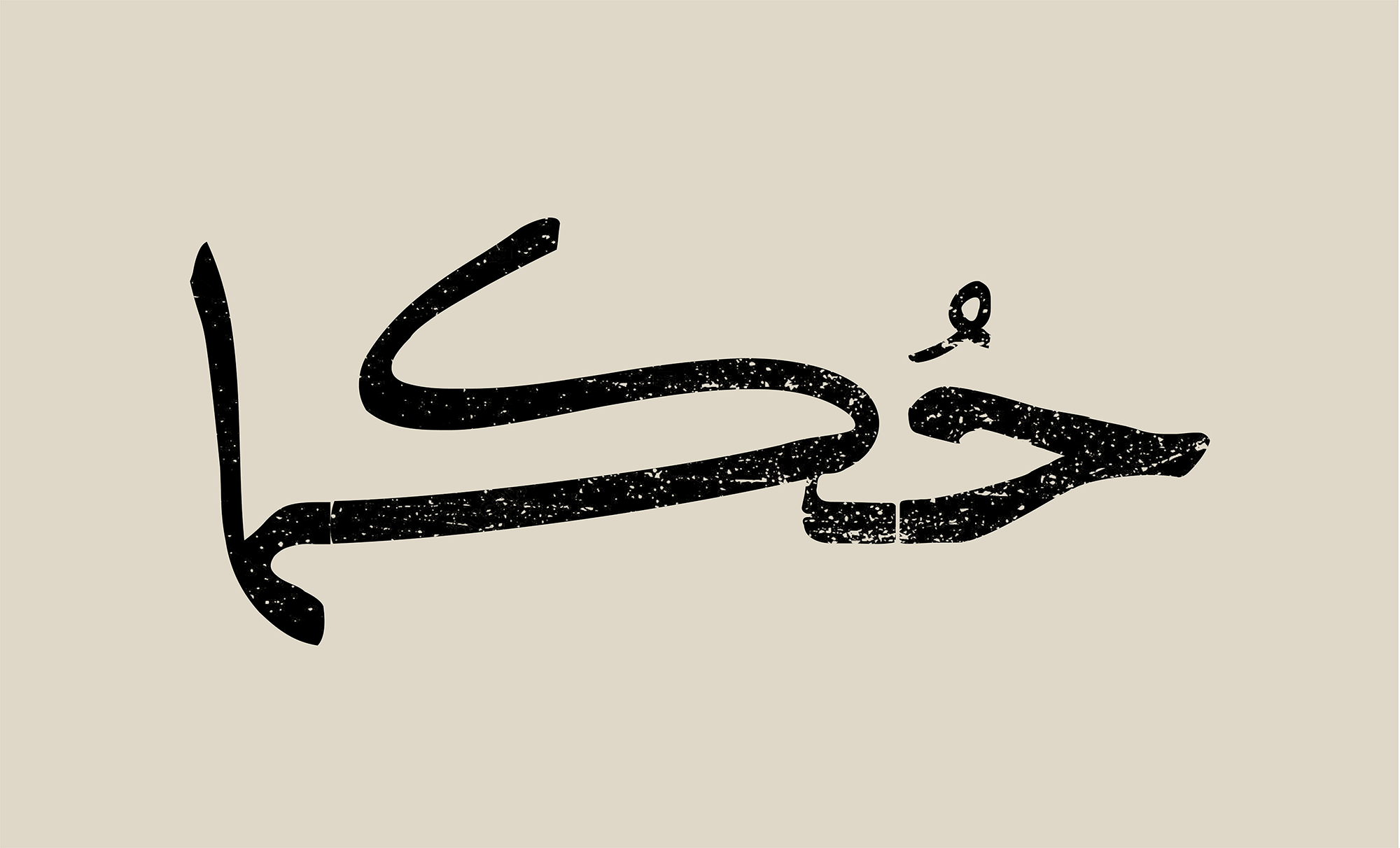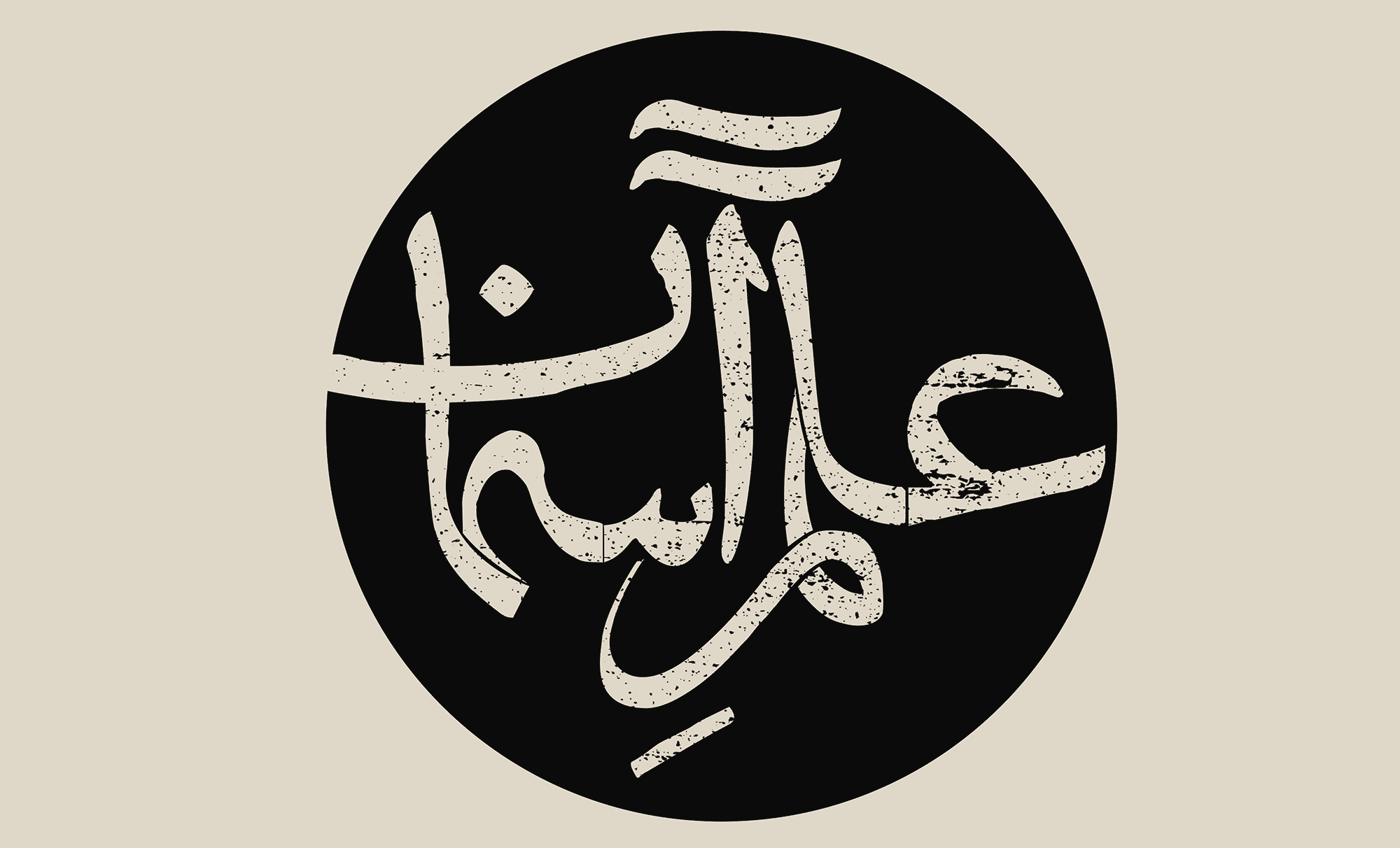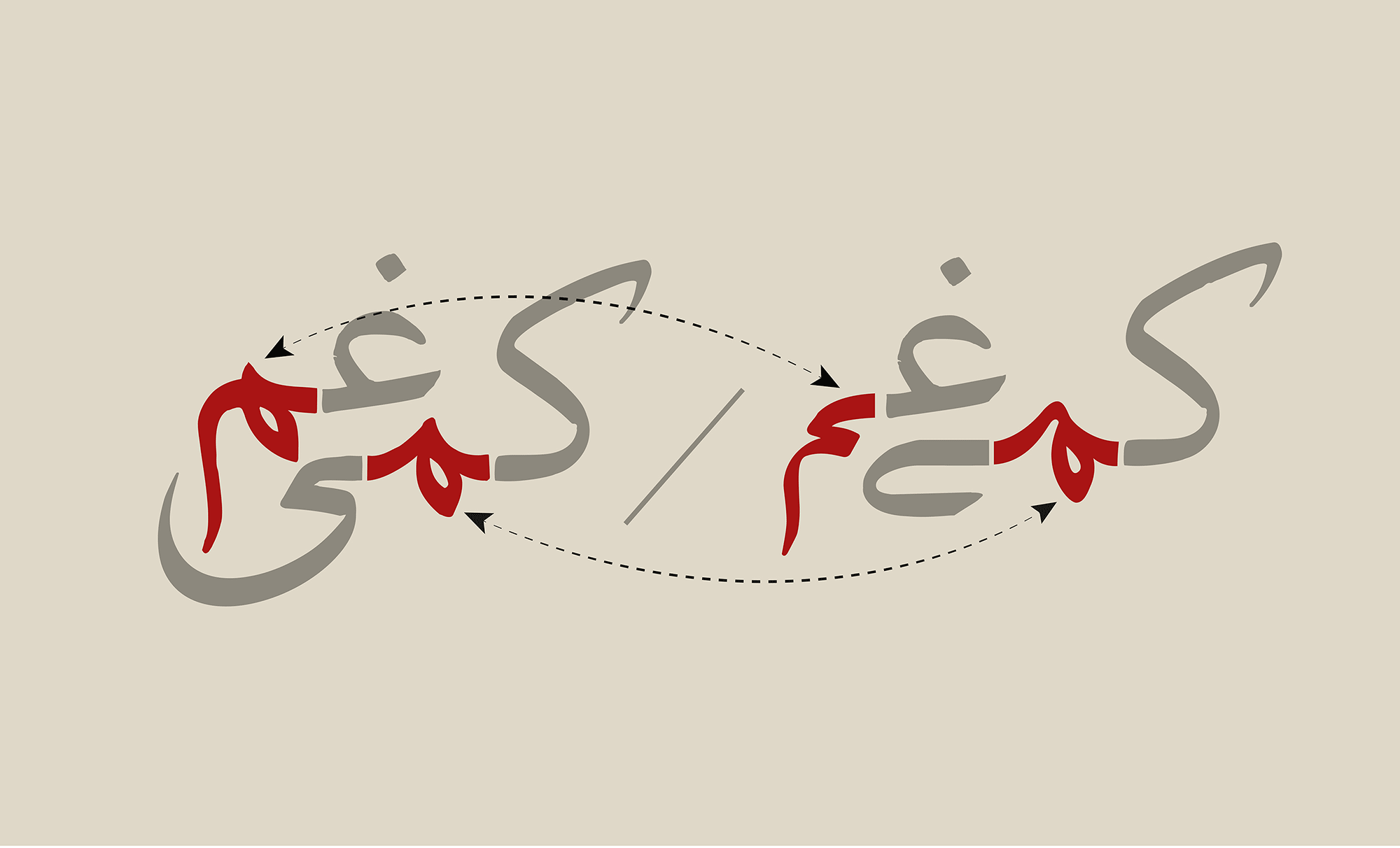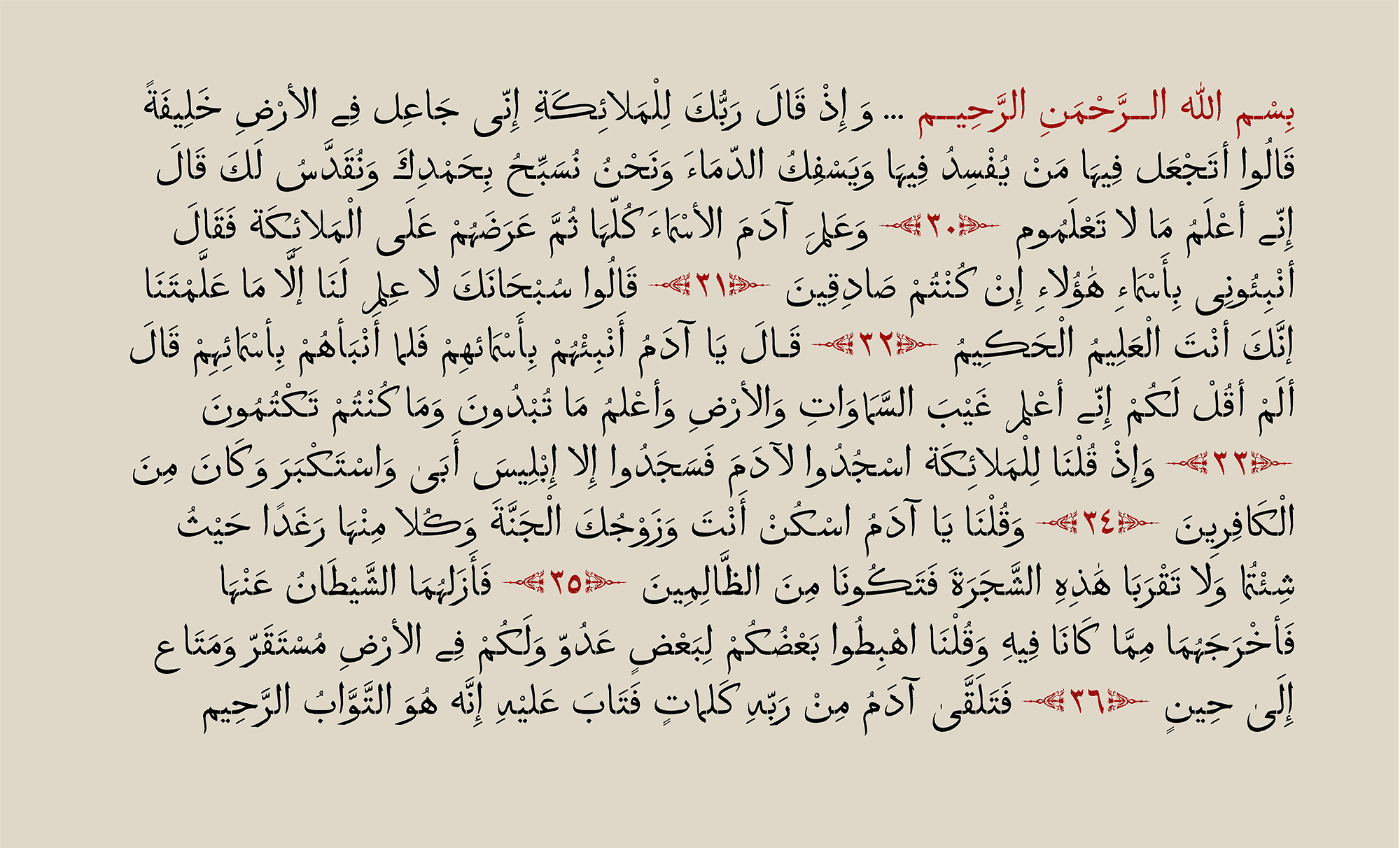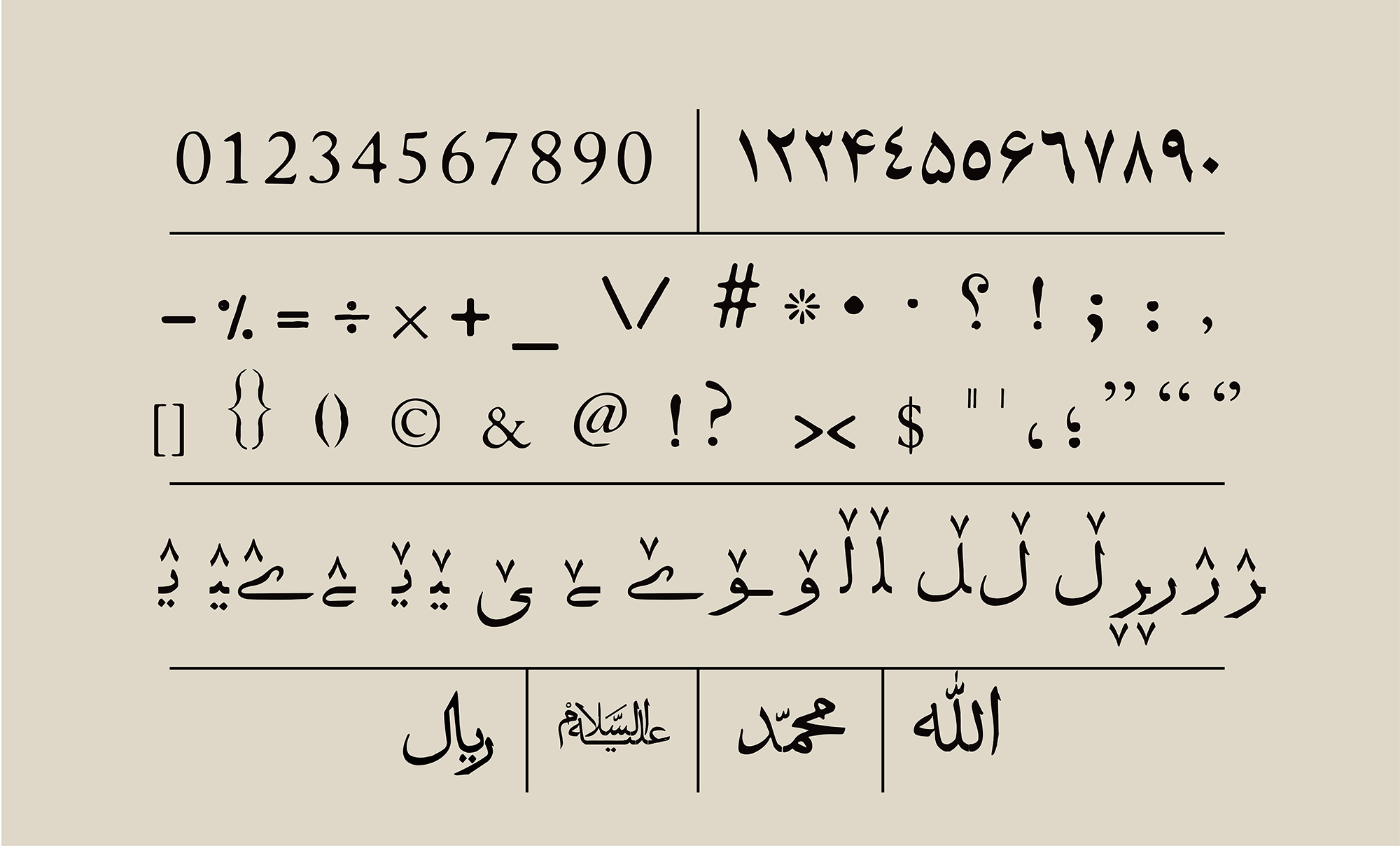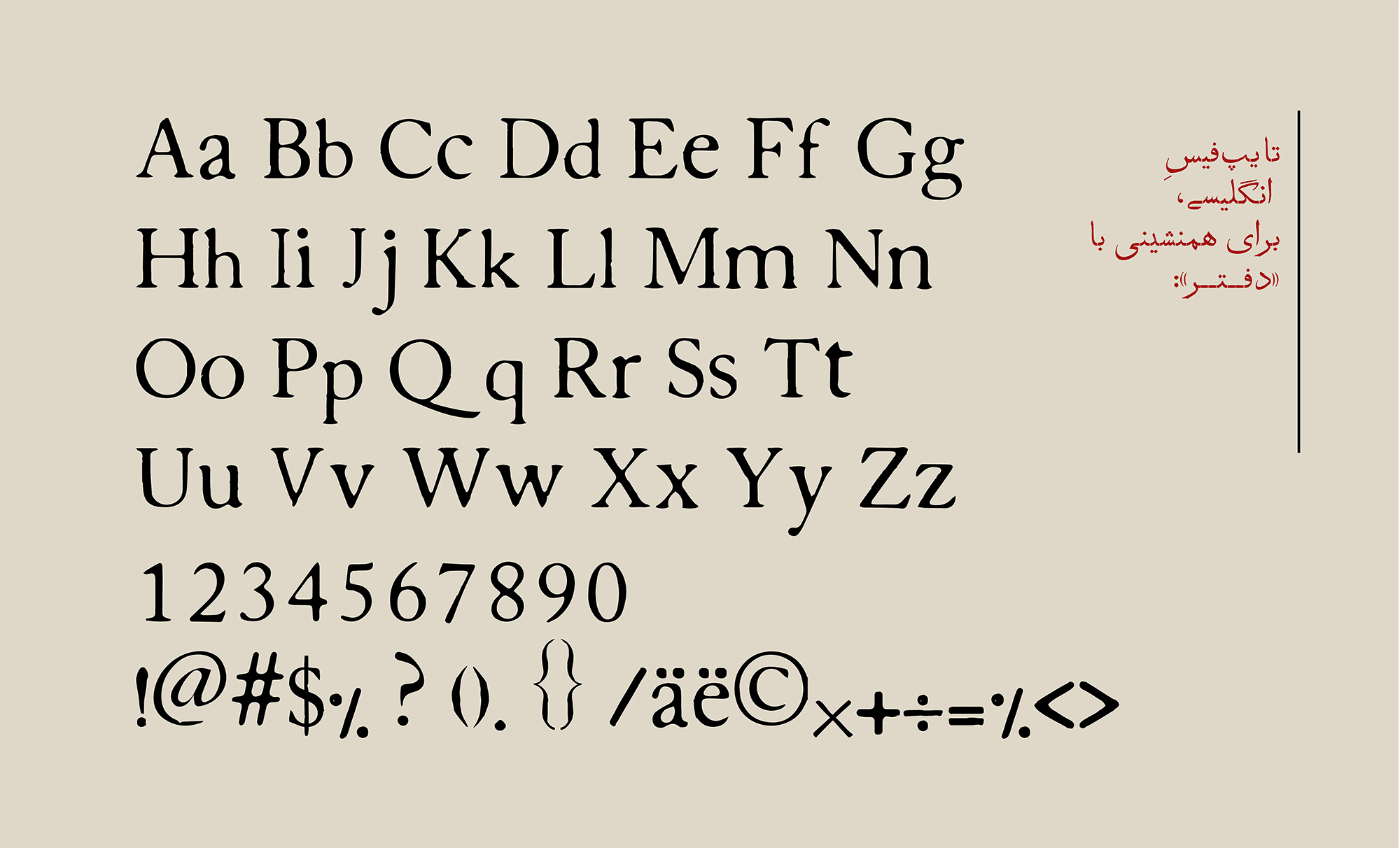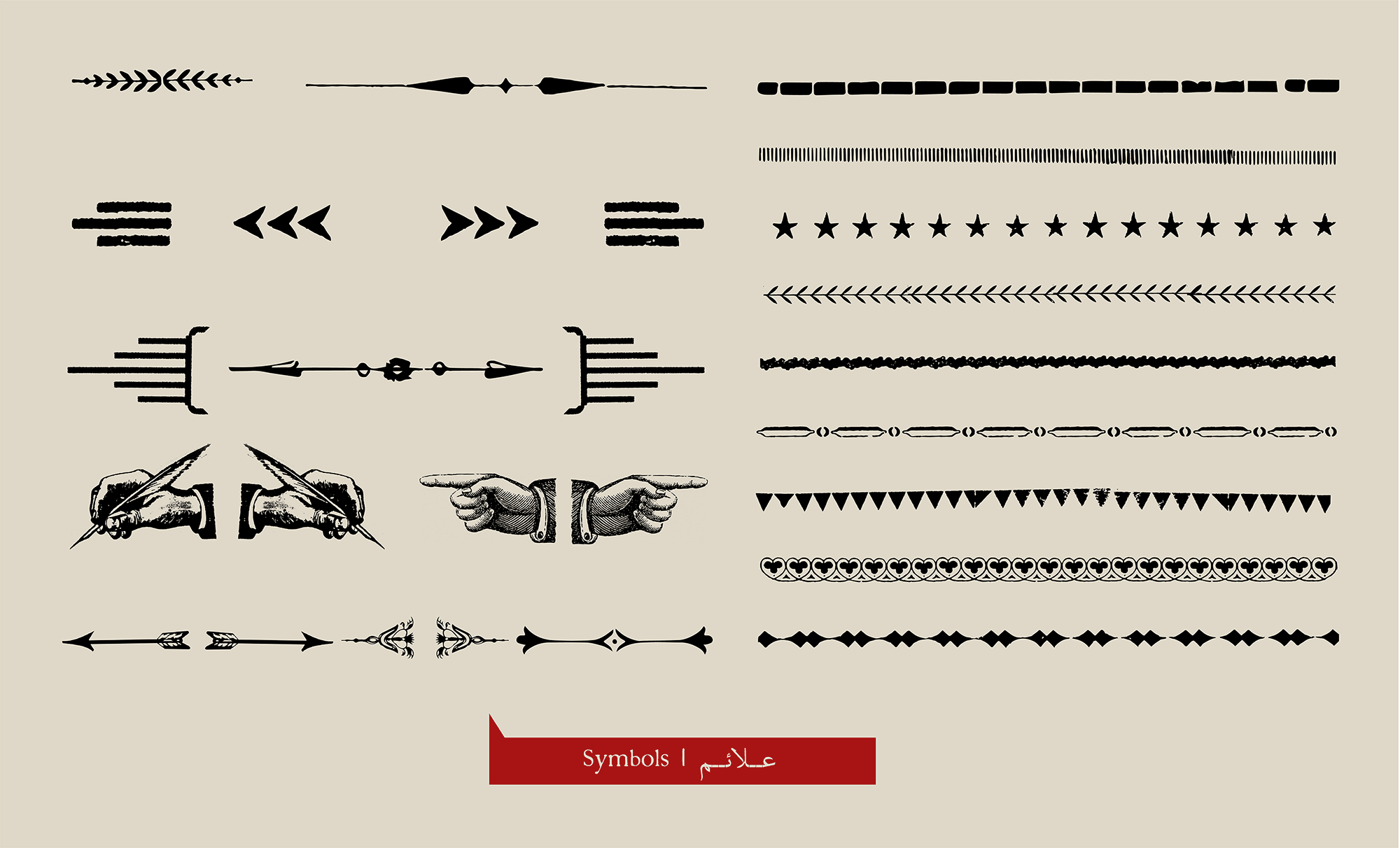
فونت دفتر در سه زبان فارسی، انگلیسی قابل استفاده است.
حروفِ تازهی کهنه!
طراحان گرافیک، طراحان فضای مجازی و وبسایت، ناشران، مطبوعات، طراحان صحنه، هنرمندان و همهی آنها که به نوعی با فونتهای فارسی سروکار دارند، همواره با کمبودِ حروفی با حال وهوای قدیمی، برای ساخت فضاهای نوستالژیک مواجه هستند.بههمین دلیل، هر وقت پای اِلقایِ حسّی قدیمی به کمک یک فونت به میان میآید، یا باید بیخیالش بشویم یا با دستکاریِ نمونههای موجود، عجالتاً کارمان را راه بیندازیم!
برشهایی از چند روزنامه/ دهه 30 شمسی
یک قرن سابقه!
قدمت این فونت که امروز؛ با نام «دفتر» نامگذاری شده است؛ به روزنامهها، آگهیها و کتابهایی برمیگردد که حدود یک قرن پیش به شیوهی «چاپ سُربی» منتشر میشدند. اوج استفاده از این حروف در اوایل دوران پهلوی اوّل بوده و هویت طرّاح احتمالی آن نامشخص است.
باخروج حروف سُربی از گردونۀ تولید، این فونت نیز رفتهرفته به محاق فراموشی رفت.
یک اعلان دولتی و یک آگهی آموزشگاه / حدود 70 سال پیش
برشهایی از چند روزنامه و کتاب / دهههای 30 و 40 شمسی
حفظ اصالت و هویت!
در طی مراحل بازسازی، به تغییر شکلی (دفرماسیون) که پروسهی چاپ سـربی با گذر زمان در ریخت حروف به وجـود میآورد وفادار بودیم. شکل حروف و اتصالات تناسب دقیقی با هم ندارند، بعـضی بهصورت صحیح بر روی خط کرسی قرار ندارند و تناسب و اندازهی حروفِ همسان لزوماً شبیه به یکدیگر نیست. در محیط و سطح حروف بافتها و خوردگیهایی مشاهده میشود که تلاش کردیم همه را حفظ کنیم. همچنین در نسخه نهایی، کاراکترهای اول، وسط، آخر و تنهای حروف، هر کدام شکل و بافتِ مختص به خود را دارند و اینطور نیست که مثلاً خانواده حروف «ص» و «ض» تنها با اضافه کردن یک نقطه ساخته شده باشند.
فرآیند بازآفرینی و بازسازی تایپفیس دفتر
وفاداری به منابع اصلی در جهت حفظ شباهت
بزرگ و کوچک/ ریز و درشت!
فونت دفتر با حفظ اصالت تصویری و پایبندی به منابع اصلی، به کمک اصلاحات و اضافه کردن امکانات جدید، نیازهای گوناگون شما را در فضای طراحی گرافیک، طراحی وب، فضای مجازی، طراحی تبلیغاتی، مطبوعاتی، کتابآرایی، طراحی هنری و… برآورده می کند. اگر چه بیشترین کاربردِ فونت دفتر در اندازههای بزرگ است، اما این فونت در حد فاصل اندازههای ریز تا ترکیبات درشت، همچنان زیبایی، خاصبودن، خوانایی و وقار خود را حفظ میکند.
ترکیبات اختیاری، حروف جایگزین/ Discretionary Ligatures
برای فونت دفتر، تعدادی ترکیب پیشبینی شده است که امکانی است برای ایجاد شکلهای متفاوت، جدید و زیبایی در حروف و کلمات. شما میتوانید این ترکیبات اختیاری را به صورت دستی فعال و استفاده کنید.
دفتر عربی!
با پیشبینی اِعرابها و برخی ترکیبات خاص، فونت دفتر می تواند از متنهای به زبان عربی پشتیبانی کند.
اعداد/ علائم/ حروف کردی
همخانوادهی انگلیسی برای دفتر
فونت انگلیسی که برای همنشینی با «دفتر» انتخاب شده است، پس از ایجاد خوردگی، بافت و تغییراتی در ترکیب، بیشترین شباهت را به همخانوادهی فارسیاش پیدا کرده تا در متون دوزبانه این جنس و شخصیت حروف متناسب و یکدست به نظر بیایند.
علائم و اَشکالِ کمکی / Symbols
در فرآیند تایپ کردن، با استفاده از علائمی که در جدول حروفِ فونت دفتر قرار داده شده ، میتوانید به جذابیت طراحی اضافه کنید.
فونت دفتر؛ سال 1396 در استودیو دفتر و زیر نظر مجید کاشانی بازسازی، اصلاح و اجرا شد. تعداد زیادی روزنامه، کتاب، مجله و آگهیهای قدیمی، منابعی بودند که برای استخراج حروف و ترکیبات مورد استفاده قرار گرفتند. این فونت اولین بار برای مدتی محدود در سایت «اهدای عضو ایرانیان» عرضه شد و همه عواید مالی آن صرف درمان بیماران نیازمند پیوند عضو شد. سرانجام پس از وقفهای حدودا سه ساله، آبان ۱۴۰۰، در وبسایت «فونتیران» عرضه میشود.